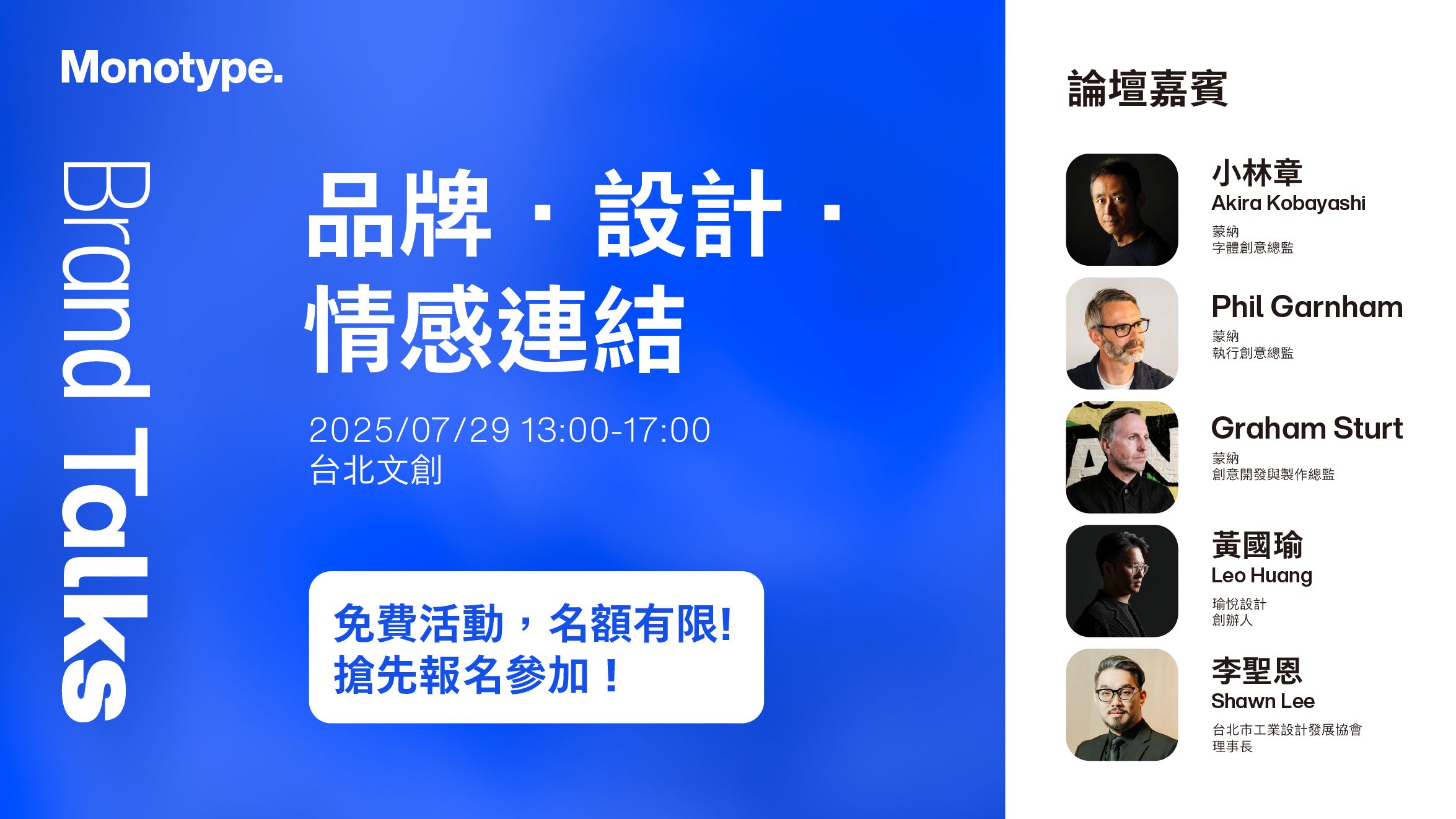
Monotype 蒙納全球系列 Brand Talks 將於七月展開亞洲巡迴,包含香港、深圳、台北與首爾。本活動匯聚來自世界各地的設計、行銷與品牌專業人士,一同探討最新趨勢、分享實用策略,並激發靈感,助力品牌邁向成功。
參與對象.
- 創意設計工作者 — 與國際頂尖設計師交流,激發靈感並提升設計表現力。
- 品牌經營者・創業者 — 透過設計與字體強化品牌的人性溫度,讓品牌在資訊爆炸時代中脫穎而出,建立長久的顧客忠誠與口碑。
- 品牌策略師・行銷人員・廣告主 — 探索設計、故事與字體如何成為品牌策略的核心,提升消費者回購率與品牌聲量。
演講介紹.
| 嘉賓 | 演講主題 |
小林章 | 從 Frutiger 到翔鶴黑體,寫下世界新經典小林章是少數有機會與字體設計傳奇 Adrian Frutiger 深度合作的亞洲設計師。他不僅參與了 Neue Frutiger、Avenir Next 等經典字型的再創作,更將 Frutiger 的人文精神與設計哲學帶入亞洲語系,創造出 Tazugane Gothic 與 M XiangHe Hei 等影響深遠的新世代字型。 英語(現場即時翻譯) |
Phil Garnham蒙納 | Revision. 現在+未來的字體設計這場分享聚焦蒙納年度活動「Revision」,Phil Garnham 將介紹字體設計的最新趨勢與未來發展,並分享來自 Sonotype、AI、Freedom、Law and Order 等主題的前瞻想法,探討字體如何隨科技與社會變遷,展現更多自由與創新可能。 英語(現場即時翻譯) |
Graham Sturt蒙納 | 從像素到人心:字體如何讓品牌更有人情味Graham 在這場分享中,會以他豐富的國際經驗,說明品牌為什麼不能只靠視覺吸睛,更要透過字體和受眾建立情感連結,讓每一次接觸都能傳遞溫度和人味,讓消費者記住「品牌帶來的感覺」。他也會分享如何透過策略性選字、設計與應用,讓品牌在資訊爆炸的時代脫穎而出,真正「講進人心」。 英語(現場即時翻譯) |
黃國瑜 | 品牌敘事品牌是對外溝通的整體形象,而溝通方式的選擇,往往決定了品牌能否被理解與感受。工具很多,關鍵在於找到最適合品牌的語言。 當我們深入理解品牌的核心,就能知道該用什麼方式說話,才能真正傳達品牌的精神。 在這當中,「字體」是一個很好的媒介。透過標準字的設計,或指定使用的字體風格,不只是美感的選擇,更是一種獨特的表達方式。 品牌的敘事,也就從這樣的細節開始慢慢展開。 |
李聖恩 | 設計前行 |
講者介紹.
| 講者 | 簡介 |
小林章 蒙納 | 小林章擁有三十多年字體設計經驗,是世界知名歐文字體設計師,2022年獲TDC獎章,被譽為「歐文字體第一人」。他曾於與 Hermann Zapf、Adrian Frutiger 合作,參與 Optima Nova、Frutiger 等經典字體設計,並創作超過五十款字體,包括 Avenir Next、DIN Next。 |
Phil Garnham 蒙納 | Phil Garnham 擁有多年全球品牌字體設計與工程經驗,現任蒙納字體創意總監,曾在 Fontsmith 領導設計專案,與團隊及國際客戶合作,善於理解品牌的創意與商業需求,並以字體建立品牌統一性。他設計過多種風格字體,強調創造性思考與線條結構的平衡。 |
Graham Sturt 蒙納 | Graham Sturt 領導全球多元化的內部創意團隊。他曾於 Interbrand、Superunion 等國際知名機構擔任創意領導職務,為 Heineken、WPP、ING、PostNL 等品牌打造屢獲殊榮的專案。Graham 的作品獲得 D&AD、Cannes Lions、European Design Awards 等國際大獎肯定,並以結合策略與設計推動創新。 |
黃國瑜 瑜悅設計 Transform Design | 瑜悅設計 Transform Design 創辦人,深耕於品牌設計領域,擅長掌握企業與品牌的樣貌,找出事物的本質並提出解決的方案。Leo 從不停止對新知識與設計方法的渴求,總是帶領著團隊不斷地思考如何再次突破。 |
李聖恩 社團法人台北市工業設計發展協會 理事長 | 現任台北市工業設計發展協會理事長,同時也是引目設計有限公司負責人與華梵大學工業設計系兼任教師,積極培育新一代設計人才。作為新燃點設計獎發起人及「而在」設計選物平台創辦人,他致力推動台灣設計產業發展,讓創意與產業接軌,帶領台灣設計走向國際。 |